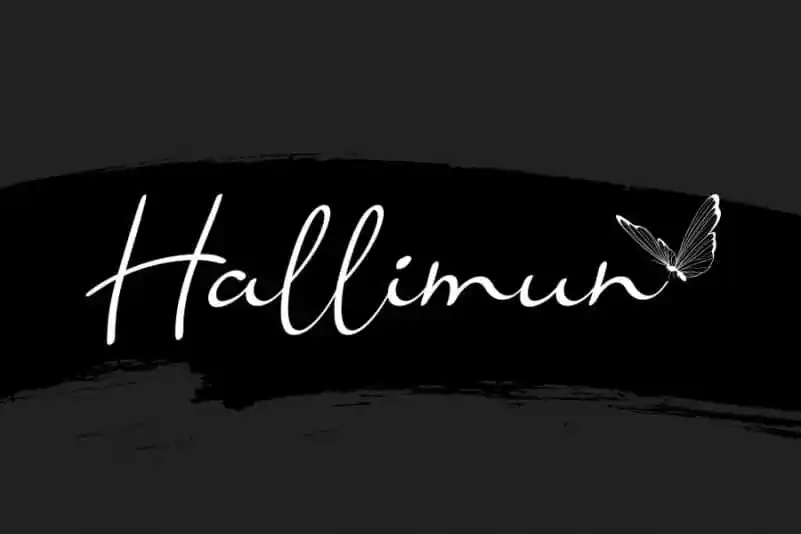
A Hallimun Script Font é uma elegante caligrafia digital projetada para revolucionar as aplicações digitais. Com seu traçado suave e natural, a Hallimun Script atinge um equilíbrio perfeito entre influências clássicas e modernidade fresca. Essa fonte vem carregada com uma vibe única que vai desde o título de uma capa até as mais sutis mensagens em um formulário digital. Perfeita para quem busca uma alternativa ao uso tradicional da caligrafia, a Hallimun Script captura a essência do handwriting em formatos digitais, proporcionando uma experiência visual única e sofisticada aos projetos. Seja você um designer gráfico ou criativo de escrita digital, não hesite em experimentar essa fonte para explorar novas possibilidades em seu trabalho.